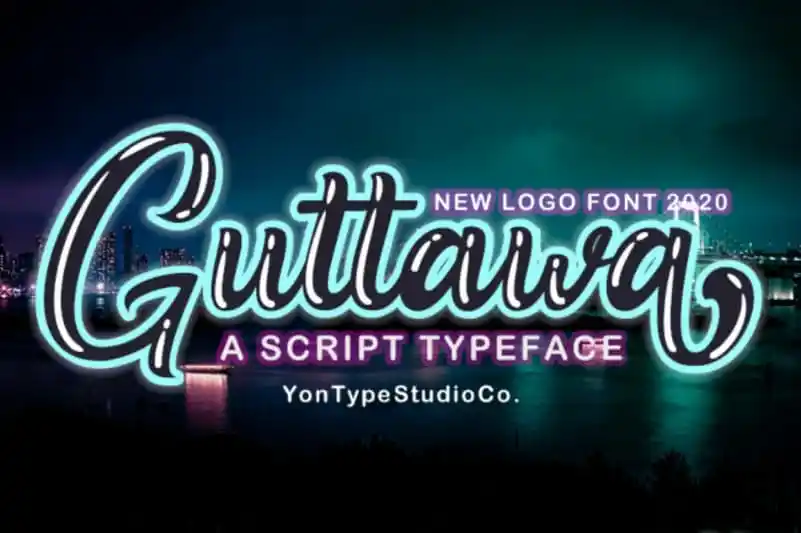
Guttawa Script Font – Download Grátis
A Guttawa Script Font é uma fonte escrita a mão que oferece uma sensação divertida e agressiva, perfeita para aqueles que procuram algo mais do que a tipografia tradicional. Este tipo de letra é única e atemporal, tornando seu uso um verdadeiro diferencial em qualquer projeto. Seja você designer de gráficos, web ou impressão, Guttawa Script é o recurso ideal para dar uma personalidade ainda maior às suas criações. Ideal para adicionar um toque único a seus projetos de arte urbana e graffiti, esta fonte foi criada pelo talentoso designer yontype, com certeza não deixará seu trabalho em silêncio.